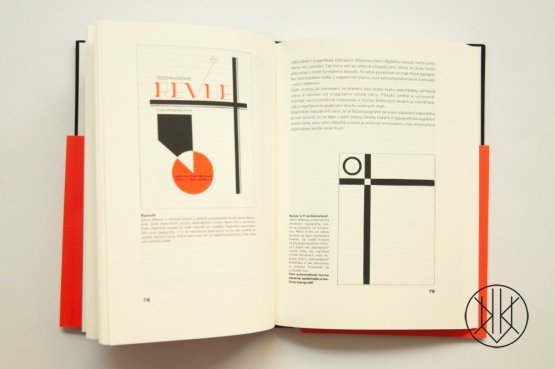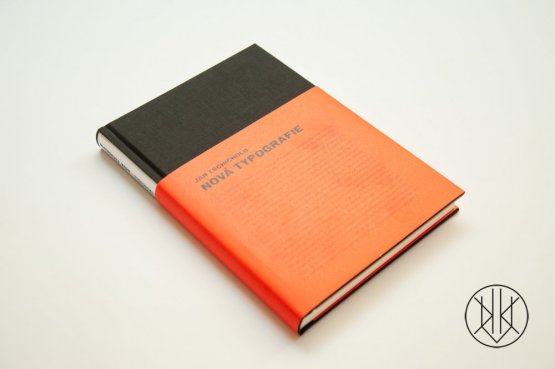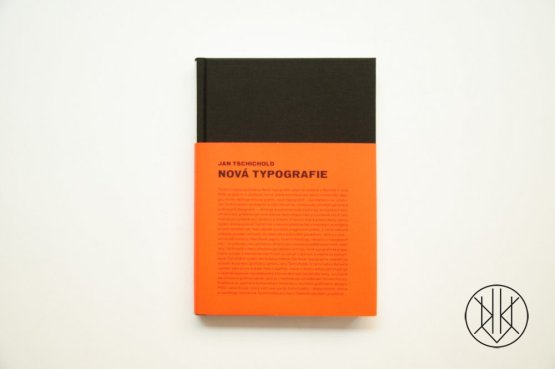
Tschicholdova publikace Die Neue Typographie vyšla poprvé v Berlíně roku 1928 a ihned se stala jedním z úhelných textů, které konstituovaly teorii moderního typografického designu a systematizovaly principy modernistické tvorby. Tschichold ve své knize představuje nejnovější dobové technologie tisku a na základě myšlenek evropských konstruktivistů definuje klíčový pojem „nová typografie“, kterou demonstruje a obhajuje na četných příkladech, jež mají zároveň posloužit jako manuál pro praktikující designéry a tiskaře.
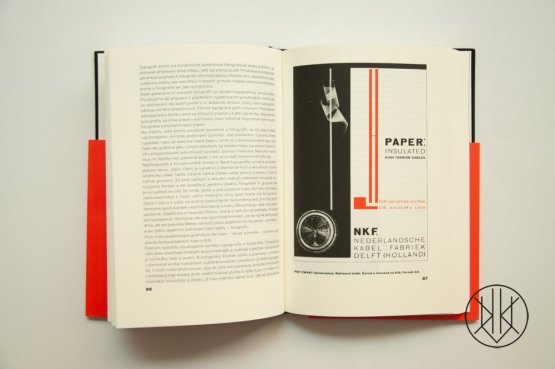V letech, které předcházely vydání Nové typografie, korespondoval Tschichold s čelnými představiteli evropských avantgard (Kurt Schwitters, El Lisickij, Moholy-Nagy, Herbert Bayer, Piet Zwart, Ladislav Sutnar aj.), od nichž získával řady ukázek jejich soudobé progresivní praxe, z nichž některé později vstoupily do obecného kulturního povědomí. První české vydání respektuje původní Tschicholdovu grafickou úpravu a je doplněno předmluvou Jana Rouse. Překlad Eva Císlerová. Grafika Jan Tschichold (historická rekonstrukce originálu David Řeřicha).
Jan Tschichold (1902–1974) je jedním z nejdůležitějších typografů 20. století. Typografii se začal věnovat už v raném věku. Vyrostl v Německu, úzce spolupracoval s Paulem Rennerem, tvůrcem písma Futura, a po vzestupu nacismu uprchl do Švýcarska. Jeho důraz na novou asymetrickou typografii a bezpatková písma byl považován za hrozbu pro kulturní dědictví Německa, které tradičně používalo typografii gotickou.